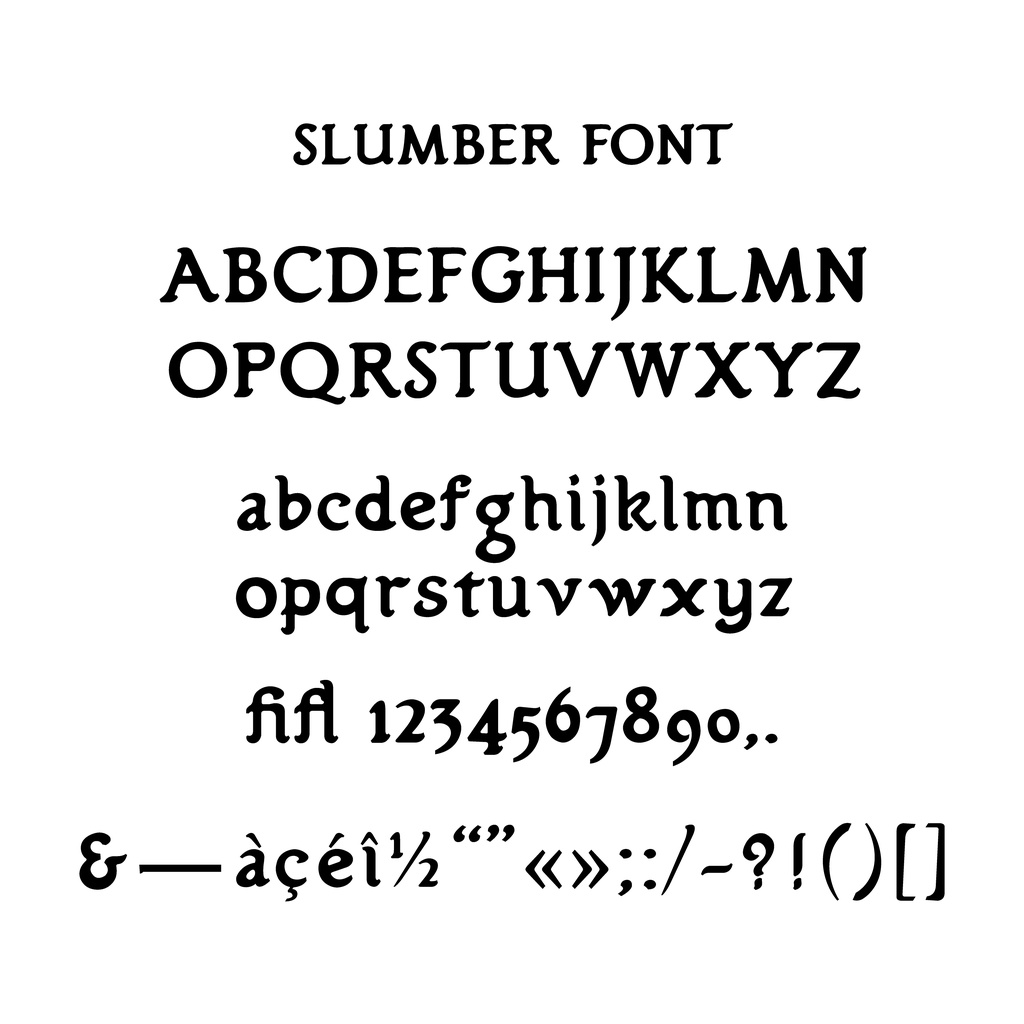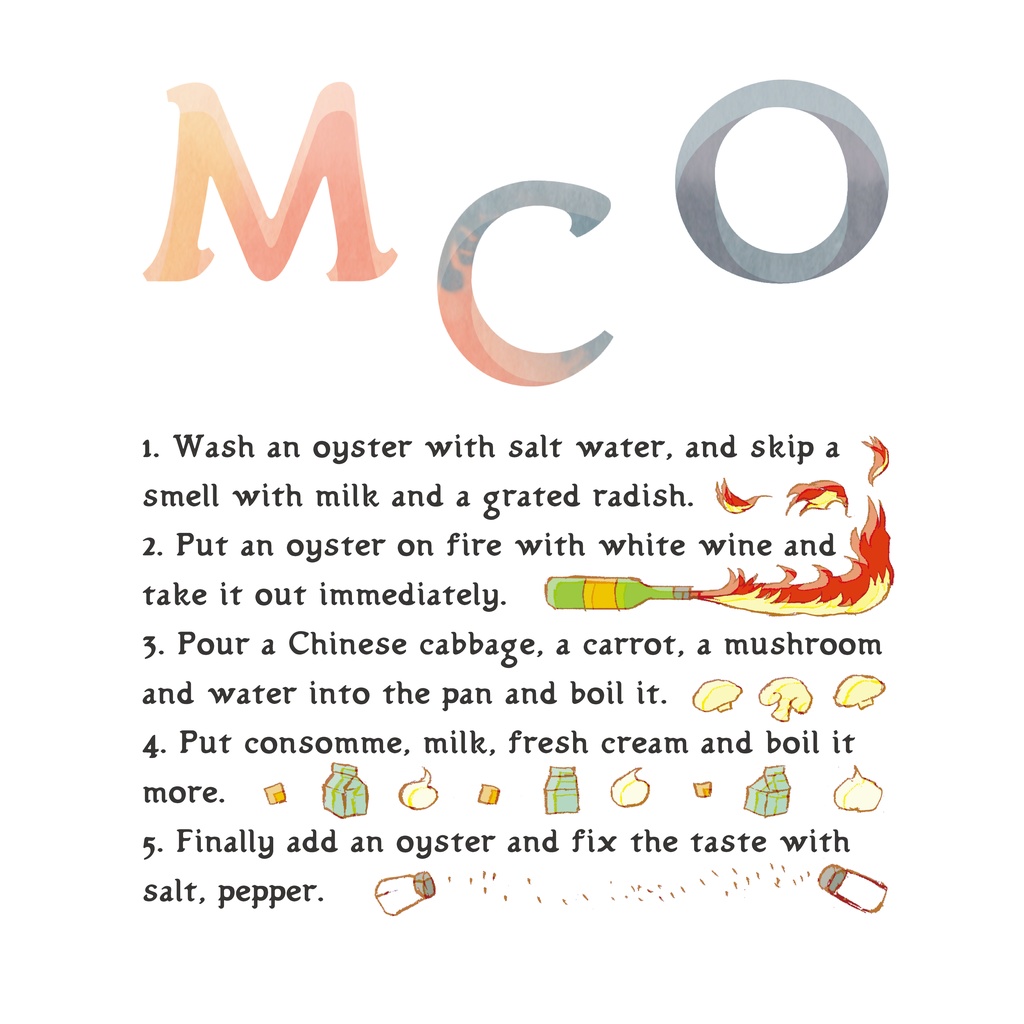
スランバーフォント
⚫︎眠りがコンセプトのフォント⚫︎ フォント名である「SLUMBER」は「まどろみ」という意味の英単語です。 眠りからくるイメージとしては、「やさしさ」「なめらかさ」などがあります。 このイメージを文字に含めるために、曲線的で有機的な形を意識しました。 参考書体:カリグラフィローマン体 【利用規約】 ・商用・非商用を問わず利用可能です。同人への利用も自由におこなってください。 ・作者は著作権を放棄していません。自作発言はご遠慮ください。 ・当フォントを利用して発生した、いかなる損害についても作者は責任を負いません。 ・フォントデータをダウンロードした時点で利用規約に同意したものとみなします。 【webフォント化、アプリや書籍などへのフォントデータの収録について】 ・サイトへ使用するためのwebフォント化やアプリへの埋め込み、書籍などへのフォントデータの収録を希望される方は、作者までご連絡ください。 ・また同時に、出典の記載をお願いしております。サイト内のどこかにダウンロードページへのリンクをご記載ください。 ・画像化しての使用、フォントデータの配布を伴わない書籍などでの使用については連絡不要です。 【禁止事項】 ・フォントデータの改変・無断転載・再配布・販売 ・当フォントを利用した制作物、ロゴなどの商標登録 【注意事項】 ・ダウンロードデータ内にはotfデータが収録されています。 ・予告なしにバージョンアップを行うことがあります。 ・一部の端末、ソフトウェアでは使用できない場合がございます。